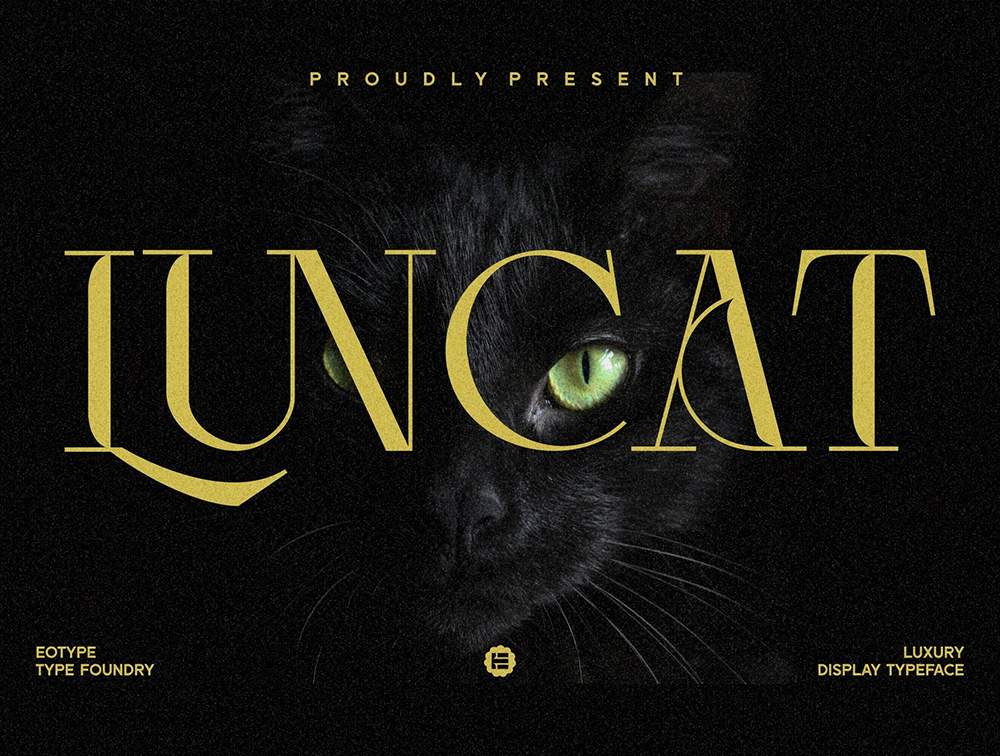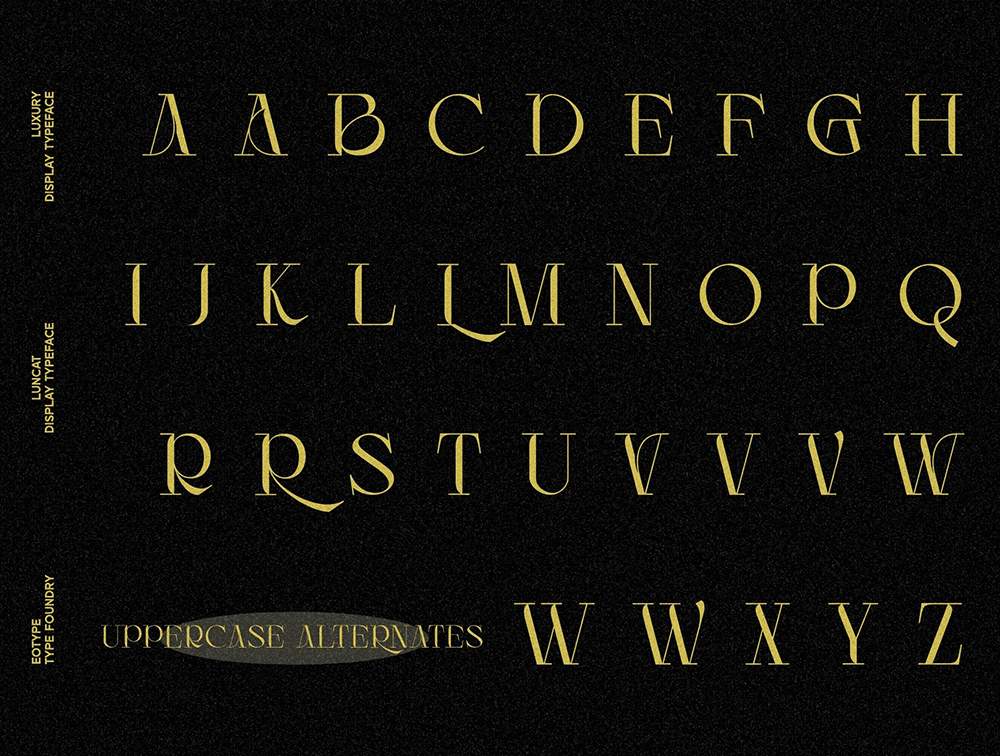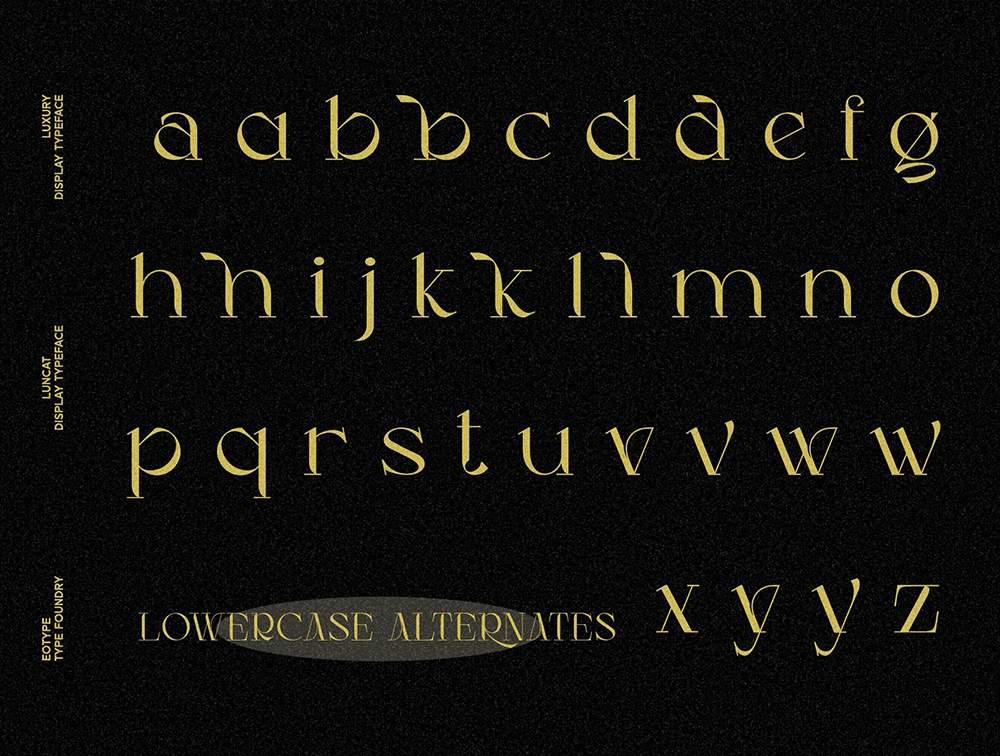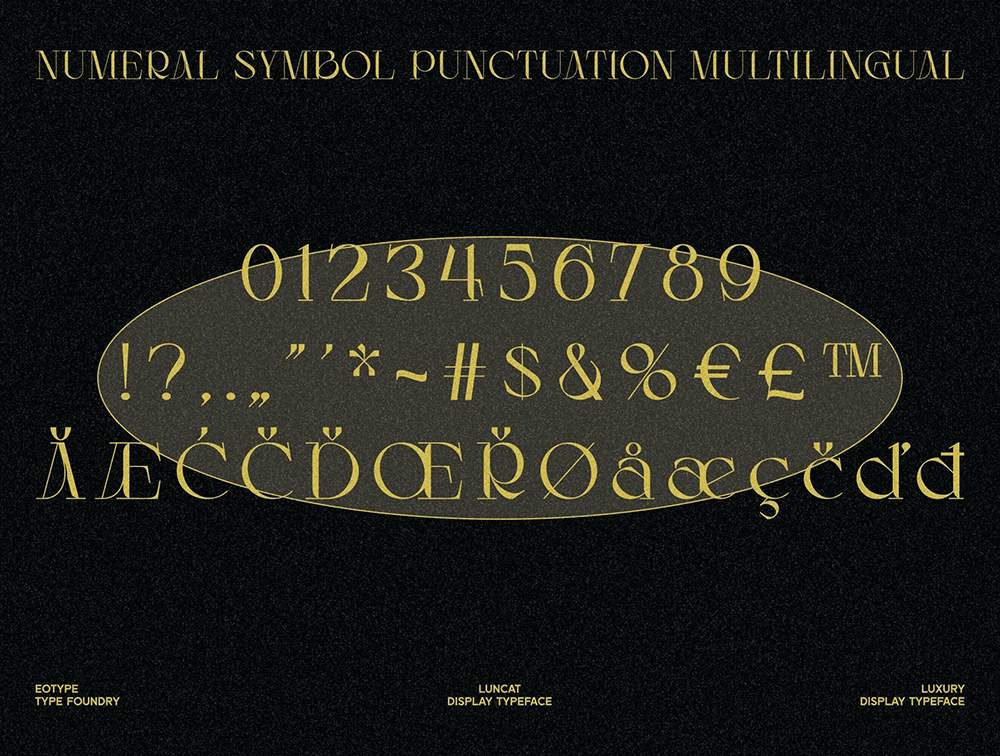
فونت پرمیوم و انگلیسی Luncat Font يک فونت سريف مدرن و فانتزی است که با تضاد شديد بين خطوط نازک و ضخيم مشخص میشود. میتوانيد از اين فونت در طرحهای مدرن قديمی استفاده کنيد. اين فونت برای انواع مختلف پروژهها مانند برندها، مجلات، لوگوها و موارد ديگر بسيار مناسب است. ويژگیهای سبک و ليگاتور جايگزين وجود دارد که باعث میشود فونت منحصر به فردتر به نظر برسد.